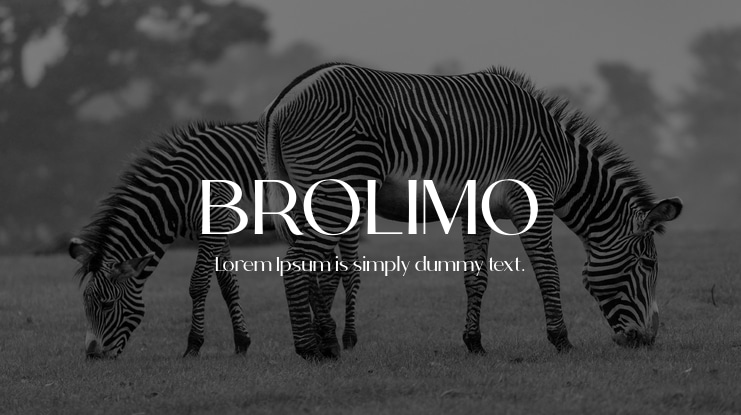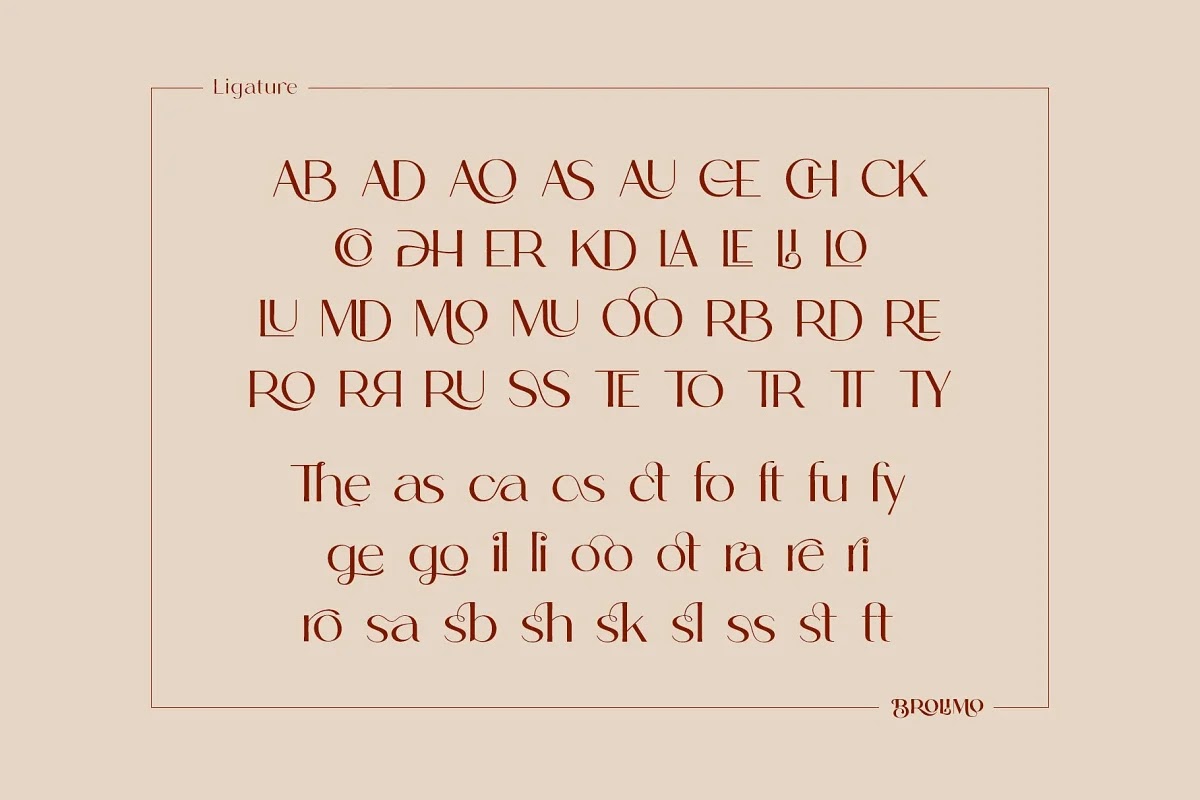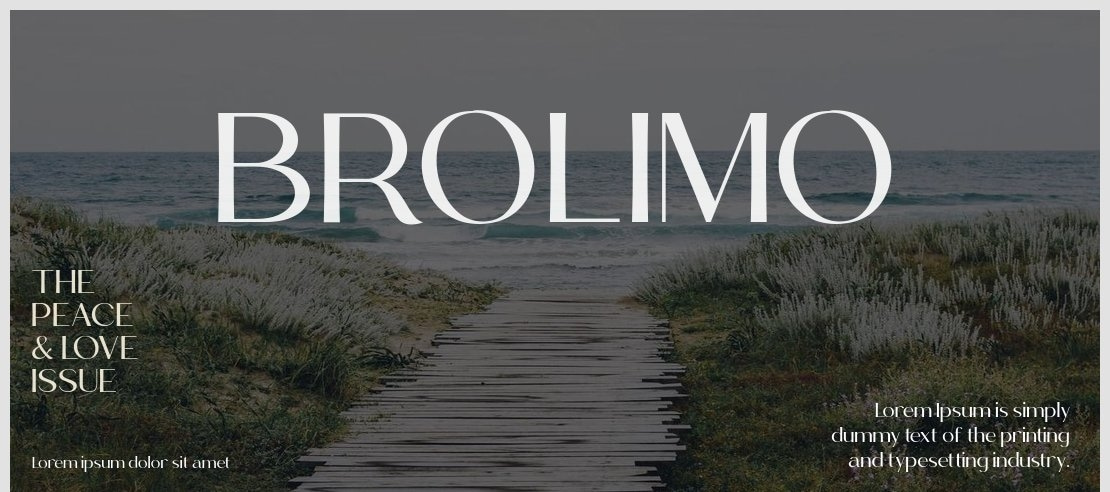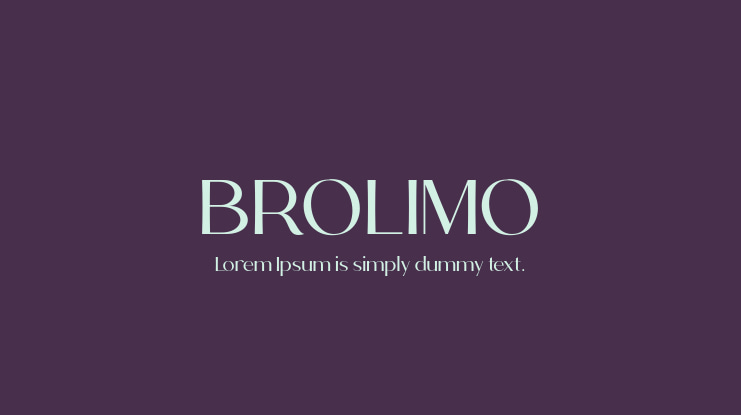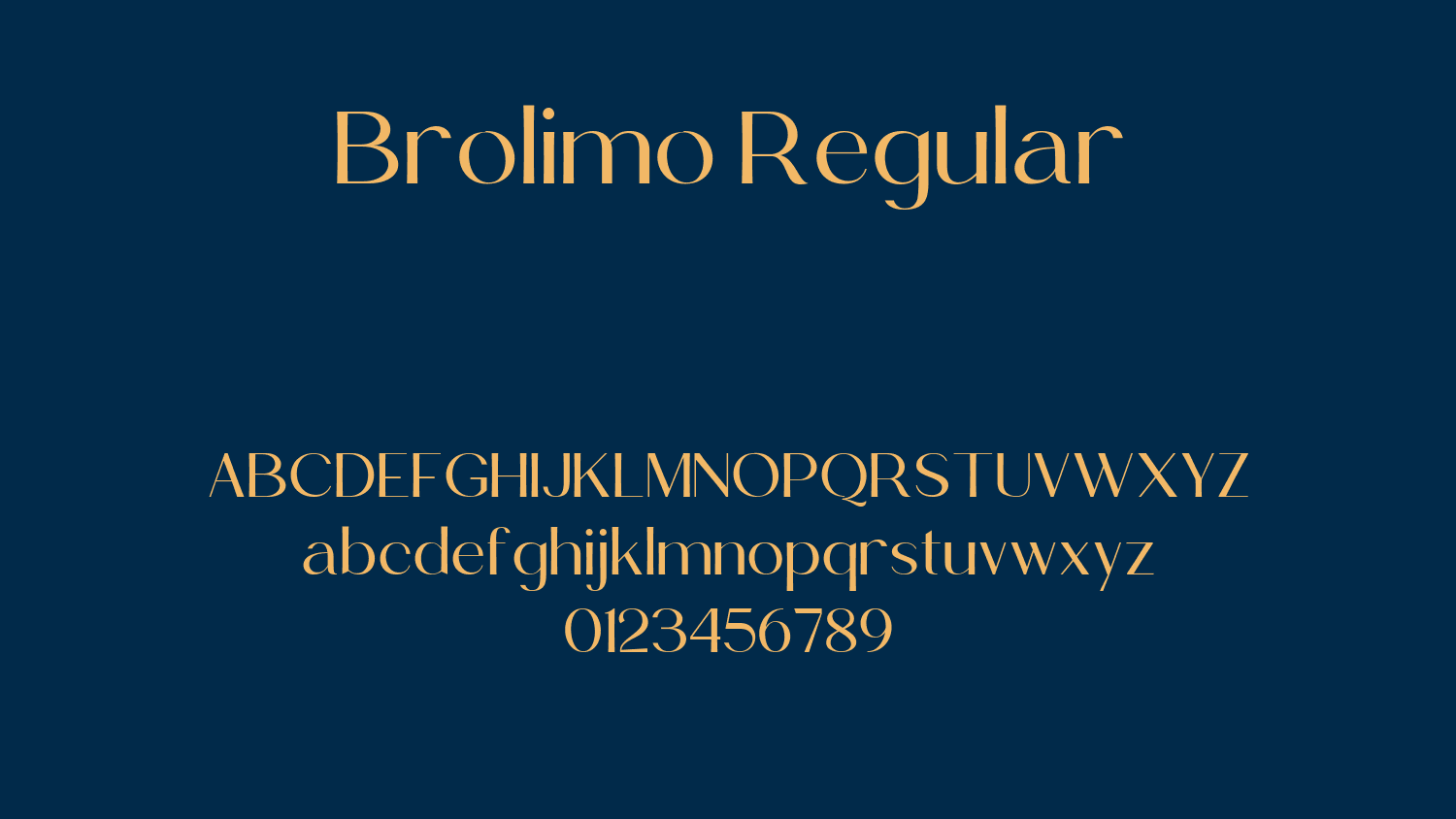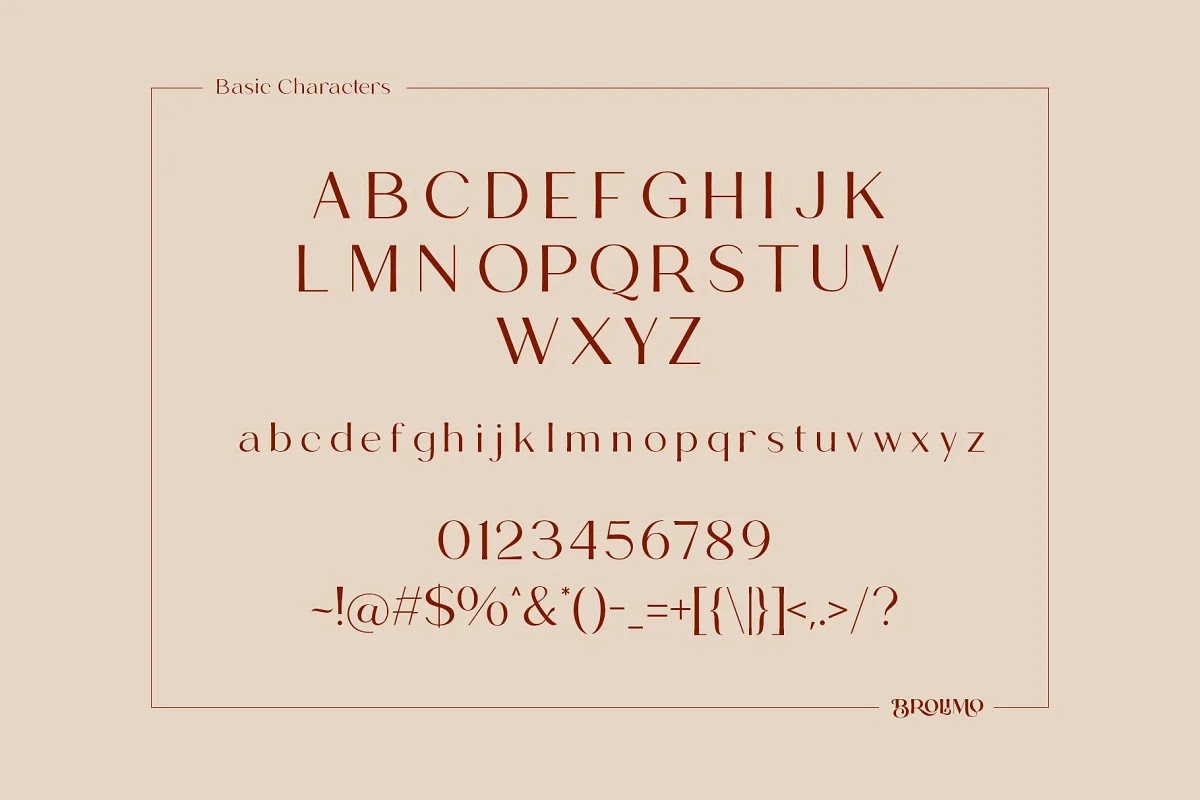
Font Brolimo là gì?
Brolimo là phông chữ thuộc dòng Modern Serif mang vẻ đẹp hòa quyện giữa nét cổ điển phương Tây và sự tinh tế của đồ họa đương đại. Đặc trưng của Brolimo là sự tương phản mạnh mẽ giữa các nét thanh mảnh và nét đậm vững chãi, đi kèm với các đường chân chữ sắc sảo.
Vẻ đẹp của Brolimo nằm ở tính thời thượng và sự hào nhoáng trong từng ký tự. Bản tải font Việt hóa Brolimo tại In Viva đã được xử lý kỹ lưỡng từng dấu thanh, đảm bảo chúng không phá vỡ cấu trúc thanh lịch của bộ chữ gốc.
Lưu ý: Brolimo có những nét thanh cực mỏng. Khi in trên bề mặt giấy mỹ thuật có gân sâu, bạn nên tăng nhẹ độ dày Stroke để đảm bảo chữ không bị mất nét do mực thấm không đều.
Sử dụng font chữ Brolimo cần lưu ý gì?
Để bản in sử dụng font Brolimo đạt độ sắc sảo cao, designer cần nắm rõ:
- Hạn chế in cỡ chữ quá nhỏ: Vì có các nét thanh mảnh, Brolimo chỉ nên dùng cho các dòng chữ từ 14pt trở lên trên bao bì để không bị mờ nhạt.